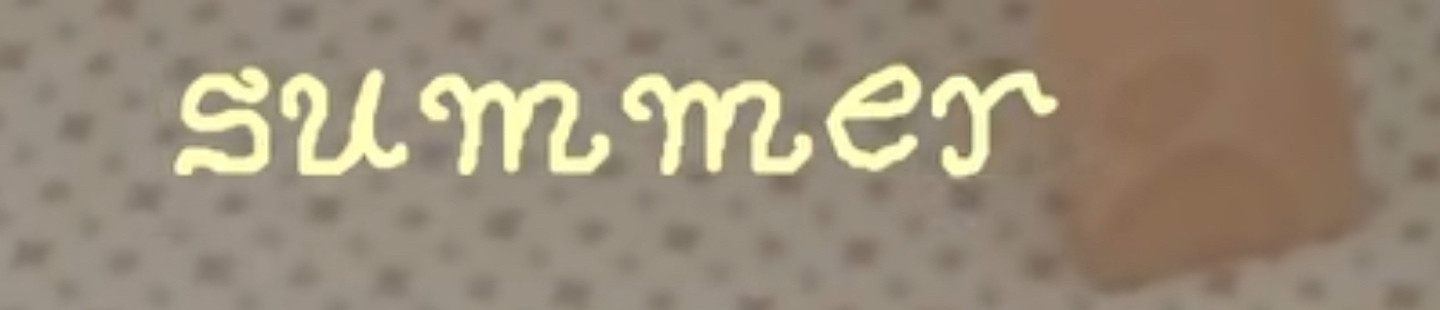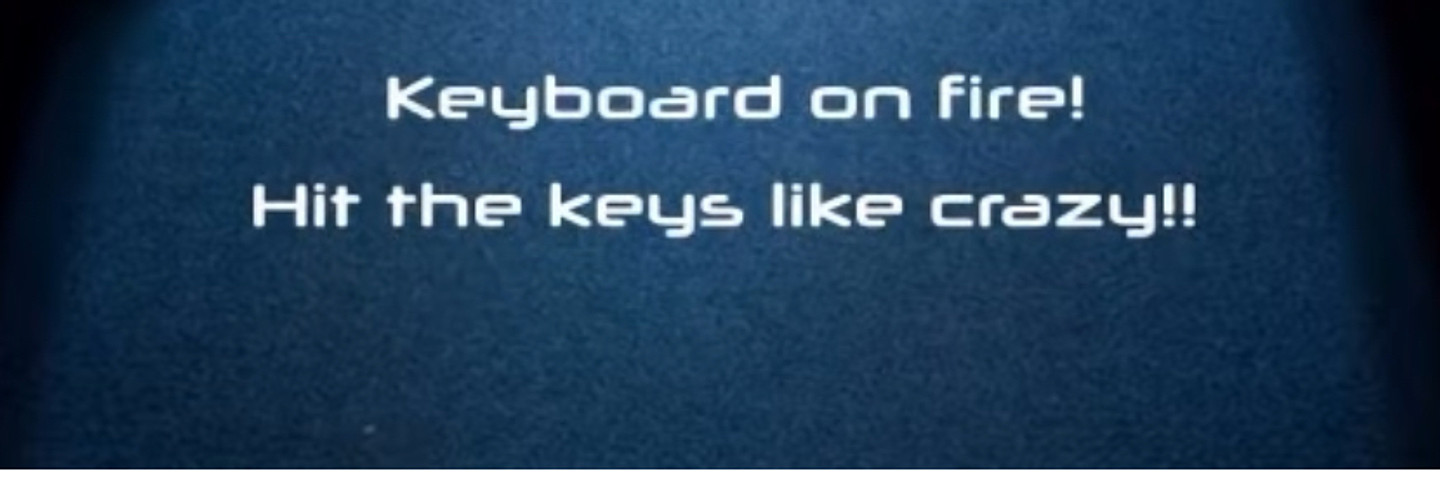
전에 작업하면서 봤던 폰트를 대략적인 기억으로 그려봤는데 이 형태와 가장 가까운 폰트가 있을까요? 제 기억이 맞다면 잠깐 일하던 곳에서 산돌 클라우드가 깔려있던 것 같습니다.
폰트 찾을 수 있을까요? 그냥 인터넷에서 주운 이미지인데.. 괄호가 완전 둥그스름 형태가 아니고 살짝 각이 있는 특징이 있습니다 ㅠㅠ